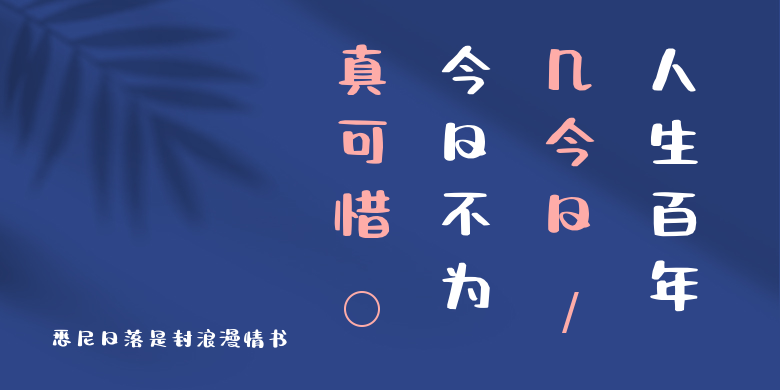
悉尼日落是封浪漫情书
悉尼日落是封浪漫情书,这款字体结构工整、笔画清晰,兼顾美观与易读性,适用于标题、正文、海报、包装、LOGO 等多种场景。字形优雅稳定,风格百搭耐看,适配日常排版与创意设计,让文字呈现更舒适、更具质感。悉尼日落是封浪漫情书一笔一画,皆是细节,以均衡的比例、流畅的线条打造舒适视觉体验,字形端正大气,风格简约现代。无论是商业设计、品牌宣传还是日常排版,都能轻松驾驭,让文字更有格调与力量。悉尼日落是封浪漫情书字体下载。